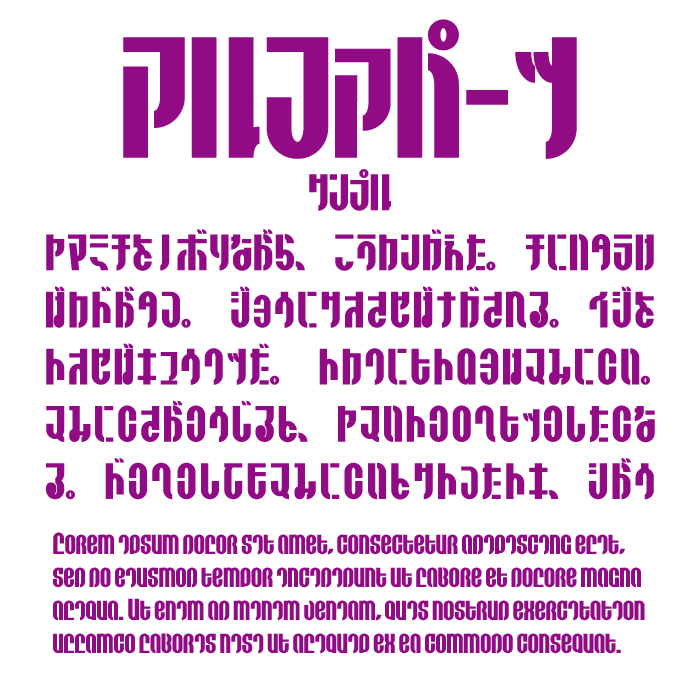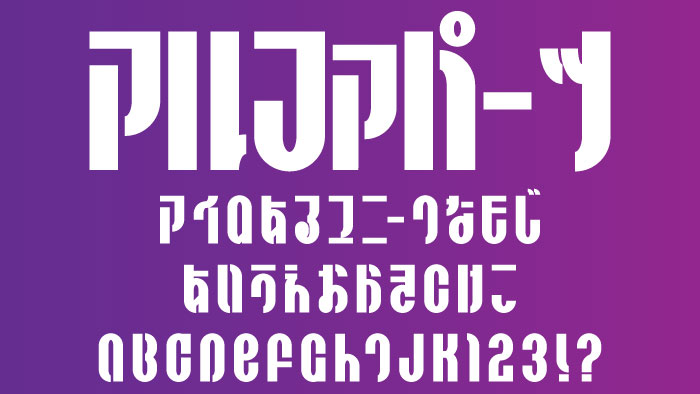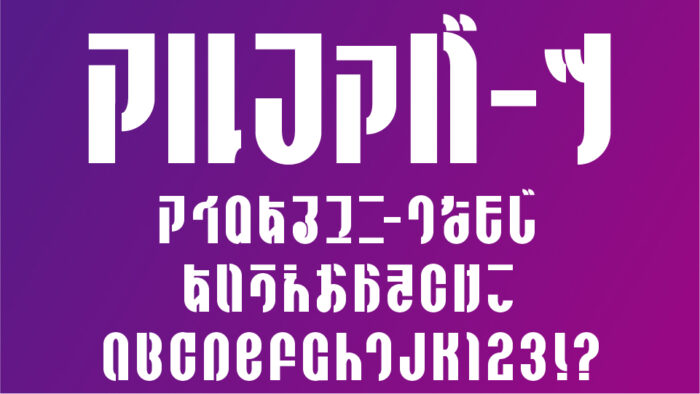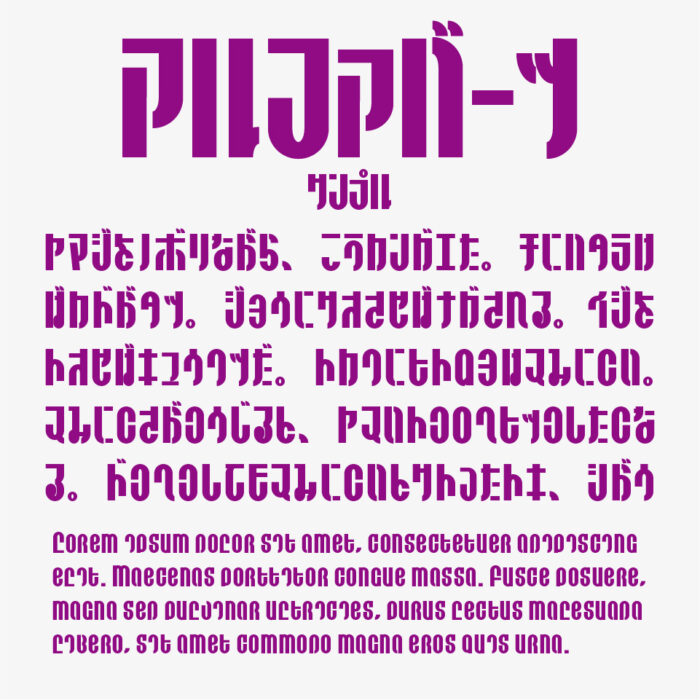
Alfapahts(アルファパーツ)フォントは、タイ文字やアルメニア文字のようにも見えるユニークなデザインフォントです。
太めで長体なフォルムで作られているフォントは、パッと見、異国の文字を思わせるミステリアスなフォントで、読めそうで読めない境界に挑んでいるようなデザインが遊び心たくさんなフォントです。
収録文字は、ひらがな・カタカナ・アルファベット・数字・記号が収録されています。